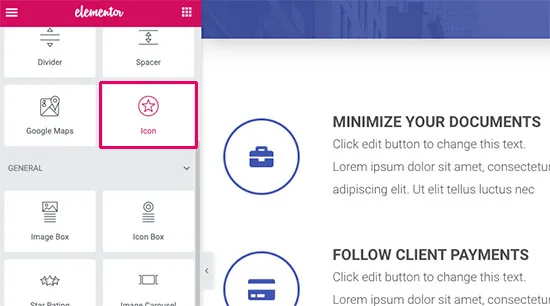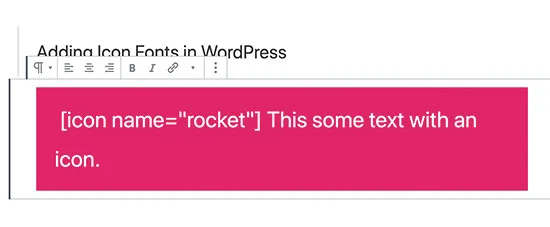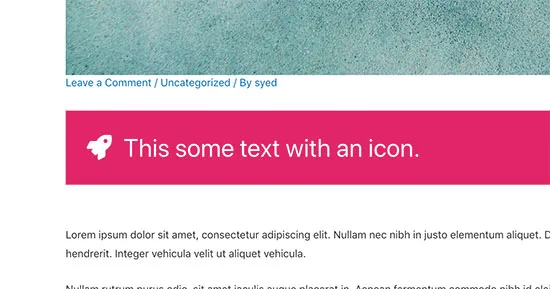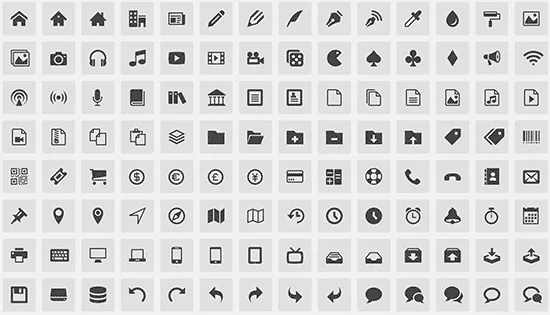
اگر میخواهید ظاهر سایتتان را چشمگیرتر کنید، یکی از بهترین کارهایی که میتوانید انجام دهید استفاده از فونت آیکونها است. این آیکونها درست مثل فونتهای معمولی روی مرورگر بارگذاری میشوند، سرعت سایت شما را پایین نمیآورند، و با CSS میتوانید هر جور که دوست دارید استایلشان بدهید. جالبتر اینکه برای استفاده از Font Awesome در وردپرس، نه به دانش برنامهنویسی نیاز دارید و نه به تجربه طراحی. در این مطلب، سه روش مختلف برای افزودن Font Awesome به وردپرس را به شما نشان میدهیم.
فونت آیکون (Font Awesome) چیست؟
فونت آیکونها در واقع مجموعهای از تصاویر برداری هستند که به شکل فونت بارگذاری میشوند. به جای حروف یا اعداد، شما یک آیکون دریافت میکنید؛ ساده، مقیاسپذیر، و سریع. اندازهشان با CSS تنظیم میشود و برخلاف تصاویر معمولی، در هیچ وضوح نمایشی تار نمیشوند.
مزیت اصلیشان نسبت به آیکونهای تصویری، سرعت است. چون به عنوان فونت بارگذاری میشوند، سربار کمتری به مرورگر تحمیل میکنند و در نتیجه سایت شما سبکتر و سریعتر کار میکند.
از آیکونهای فونت میتوانید در بخشهای مختلف سایت استفاده کنید: سبد خرید، دکمههای دانلود، جعبههای ویژگی، منوها، شبکههای اجتماعی و هر جایی که یک آیکون میتواند محتوای شما را گویاتر کند. ضمناً این آیکونها با تقریباً تمام مرورگرهای مدرن سازگار هستند، پس نگران مشکل نمایش نباشید.
روش های استفاده از فونت آیکن ها در وردپرس
روش های مختلفی برای افزودن Font Awesome به قالب وردپرس وجود دارد که ما در ادامه مطلب قصد داریم چند مورد از آنها را به شما آموزش دهیم. همراه ما باشید.
1- استفاده از افزونه (سادهترین روش)
اگر شما مبتدی هستید و می خواهید از آیکون های مختلفی در پست ها و صفحات سایت خود استفاده کنید، ساده ترین و سریع ترین روش استفاده از یک افزونه وردپرس می باشد. با استفاده از این روش نیازی نیست تغییراتی در فایل های قالب خود اعمال کنید و می توانید از فونت های آیکون در هر قسمتی از سایت خود به سادگی استفاه نمائید.
پس از فعال سازی افزونه اکنون می توانید هر پست یا صفحه وردپرس را ویرایش کنید و از کد کوتاه آیکون مانند زیر استفاده نمائید:
می توانید از این کد کوتاه همراه با متن دیگر یا به تنهایی در یک بلوک کد کوتاه اختصاصی استفاده نمائید.
پس از افزودن، می توانید پیش نمایش پست یا صفحه خود را مشاهده کنید تا ببینید آیکون ها چگونه در سایت شما به نظر می رسند. به عنوان مثال: در تصویر زیر یک نمونه فونت آیکون را مشاهده می کنید:
همچنین می توانید کد کوتاه آیکون فونت را در یک بلوک پاراگراف اضافه نمائید.
2- استفاده از صفحهسازها
اکثر افزونه های صفحه ساز وردپرس دارای ویژگی فونت آیکون می باشد که شما می توانید به سادگی از آنها در صفحات مختلف سایت خود استفاده کنید.
– اضافه کردن فونت آیکون در وردپرس با صفحه ساز Beaver Builder
افزونه Beaver Builder یکی از افزونه های محبوب صفحه ساز برای وردپرس می باشد که به شما این امکان را می دهد تا به راحتی طرح بندی صفحات سفارشی را در وردپرس بدون نوشتن هیچ کدی ایجاد کنید. همچنین این افزونه دارای مجموعه ای از آیکون های زیبا و ماژول های آماده برای استفاده است که می توانید آنها را بکشید و در پست و صفحات خود رها کنید.
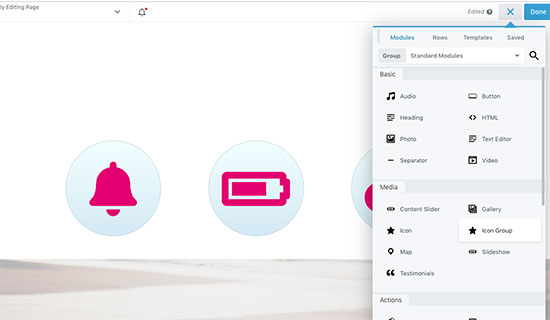
میتوانید گروه های آیکون ایجاد کنید، یک نماد واحد اضافه نمائید و آنها را به ردیف ها و ستون هایی با موقعیت مناسب انتقال دهید. علاوه بر آن شما همچنین می توانید رنگ بندی، پس زمینه، فاصله، حاشیه و غیره هریک از آیکون های خود را سفارشی نمائید.
– اضافه کردن فونت آیکون در وردپرس با صفحه ساز المنتور پرو
بی تردید یکی از بهترین و پرطرفدارترین افزونه صفحه ساز وردپرس جهان که محبوبیت بسیار بالای را در بین کاربران به دست آورده، افزونه المنتور پرو می باشد. این افزونه به شما این امکان را می دهد تا به سادگی فونت آیکون های مختلفی را در سایت خود قرار دهید.
تنها کاری که شما باید انجام دهید این است که یک آیکون را بکشید و در موقعیت دلخواه رها کنید. همچنین می توانید از ردیف ها، ستون ها و جداول برای ایجاد صفحات زیبا استفاده نمائید.
3- افزودن دستی Font Awesome
همچنین شما می توانید کل فهرست فونت را در یک پوشه در قالب وردپرس خود آپلود کنید و سپس از آن فونت ها در شیوه نامه خود استفاده نمائید. در ابتدا وارد وب سایت Font Awesome شوید و سپس آدرس ایمیل خود را برای دریافت کد جایگذاری فونت وارد نمائید.
پس از اینکه آدرس ایمیل خود را وارد و روی گزینه ارسال کلیک کردید، یک ایمیل همراه با یک کد برای شما ارسال می شود. سپس این کد را شما باید درست قبل از تگ </head> در فایل header.php قالب وردپرس خود کپی و جایگذاری نمائید. کد شما همانند زیر خواهد بود:
این روش بسیار ساده است، اما از طرفی می تواند باعث تداخل با سایر افزونه ها شود. یک رویکرد بهتر، بارگیری صحیح جاوا اسکریپت در وردپرس با استفاده از مکانیزم صف بندی داخلی می باشد. برای انجام دادن اینکار، شا می توانید کد زیر را در فایل functions.php قالب خود یا در یک افزونه مخصوص سایت اضافه نمائید:
افزودن فونت آیکون به وردپرس یکی از سادهترین و مؤثرترین کارهایی است که میتوانید برای بهبود ظاهر سایتتان انجام دهید. در این مطلب سه روش را با هم بررسی کردیم: استفاده از افزونه برای تازهکارها، استفاده از صفحهسازهایی مثل Beaver Builder و المنتور پرو برای کار بصری، و افزودن دستی برای کسانی که کنترل بیشتری میخواهند. هر سه روش کار میکنند؛ فقط بستگی دارد که چقدر با وردپرس آشنایی دارید و چه رویکردی برای شما راحتتر است. امیدواریم این آموزش برایتان مفید بوده باشد.